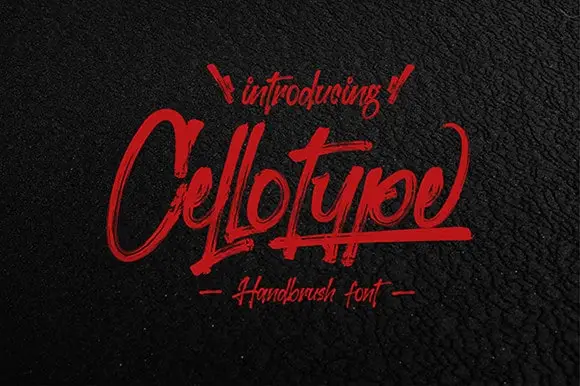
Cellotype Brush Font
A “Cellotype Brush Font” é uma tipografia a esmalte que traz a essência do estilo artesanal sem comprometer a funcionalidade para projetos profissionais. Com 2 estilos distintos, ela oferece um toque único e lindo em cada letra, inspirado na escrita a mão, tornando-a perfeita tanto para marcas de empresa quanto para logotipos, roupas, camisetas, capas de hoodie, embalagens de produtos, frases, flyers, panfletos, anúncios e muitos outros materiais. Essa fonte é uma ótima escolha para quem busca um toque único em seus projetos de design, sem comprometer a estética ou legibilidade.
Designer: Opand